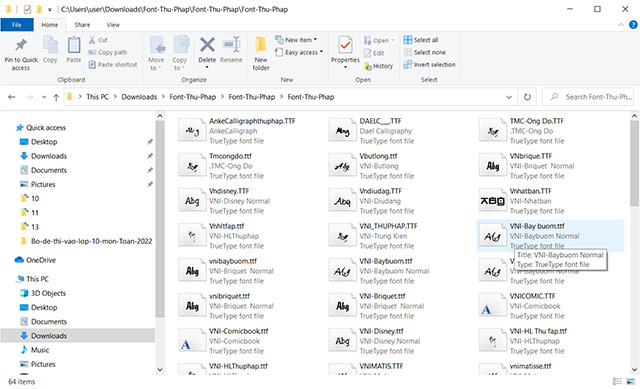
Bộ Font Thư pháp Hỗ trợ viết thư pháp, câu đối đẹp
Bộ Font Thư pháp gồm 64 Font chữ Thư pháp Tiếng Việt, hỗ trợ viết chữ thư pháp, câu đối đẹp như một nghệ sĩ thực thụ. Đặc biệt, nét mực được tạo ra giống như khi dùng bút mực viết chữ lên giấy mà các ông đồ vẫn thường dùng.
Bộ Font Thư pháp
Để học viết chữ pháp thì không hề đơn giản, mất rất nhiều thời gian để rèn luyện. Thế nhưng, với bộ font chữ thư pháp này, bạn nhanh chóng tạo được những dòng chữ nghệ thuật đẹp mắt ngay trên máy tính của mình. Ngoài ra, có thể tham khảo thêm bộ font Unicode, Font VnTime.